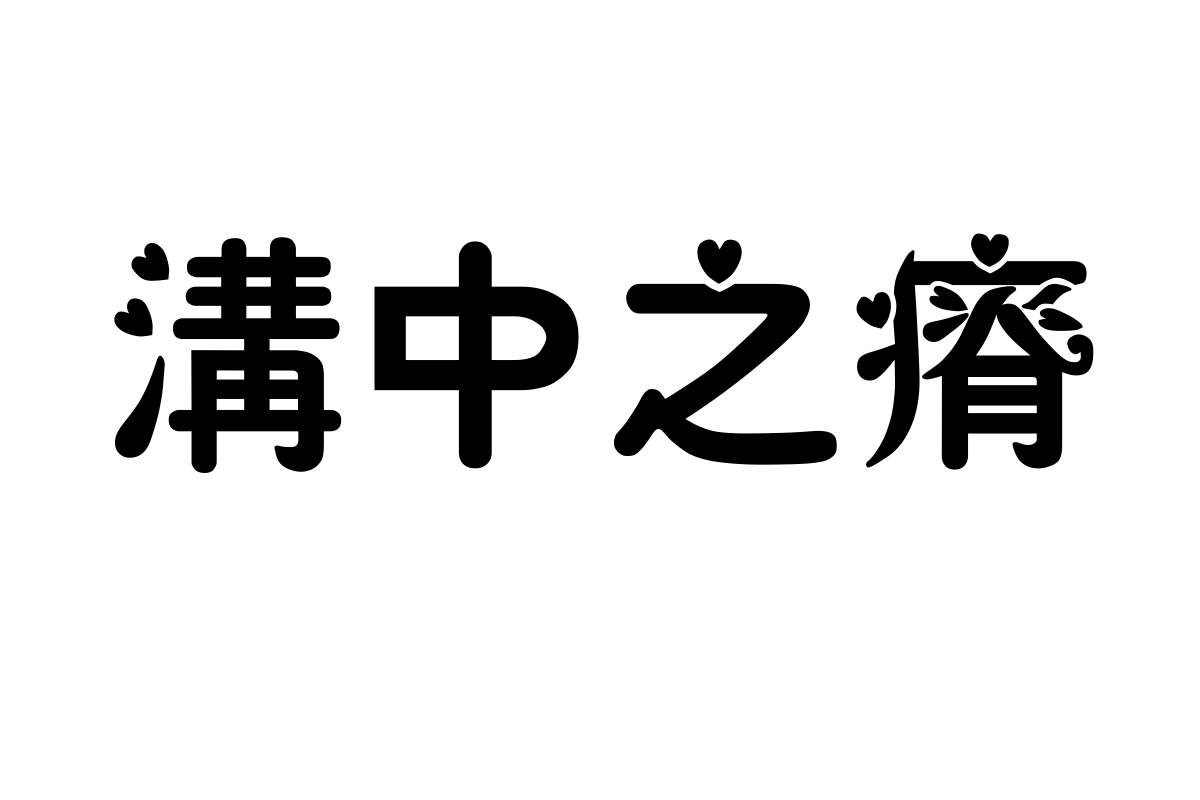
汉仪秀英体是一套适用于多种应用场景的中文字体,由汉仪公司设计。它的特点是字形优美、结构均衡,适合用于广告、书籍、杂志、报纸等各种印刷品。这款字体具有很高的辨识度和可读性,能够很好地展现文字的美感和信息内容。同时,汉仪秀英体还注重细节的处理,使得整体看起来更加精致和优雅。无论是企业品牌标识还是个人作品,选择汉仪秀英体都能展现出独特的魅力和风格。